星海社×Amazon×字游工房による世界初となる星海社オリジナルの「電子書籍専用フォント」による電子書籍が7月17日に販売開始
世界初となる星海社オリジナルの「電子書籍専用フォント」の書体設計は、スティーブ・ジョブズの賞賛を受けたmacOS標準搭載日本語フォント・ヒラギノの書体設計士である字游工房の鳥海修氏。「心を揺さぶる」をテーマにしたフィクション用かなフォント「フミテ(筆)」と、「頭が冴え渡る」をテーマにしたノンフィクション用かなフォント「なぎ(凪)」は、それぞれのフォントの開発アドバイザーを務めた作家・京極夏彦氏とライター・古賀史健による命名となる。電子書籍化にあたってのディレクションは星海社の紺野慎一氏、松島智氏が務めた。
電子書籍専用フォント「フミテ(筆)」
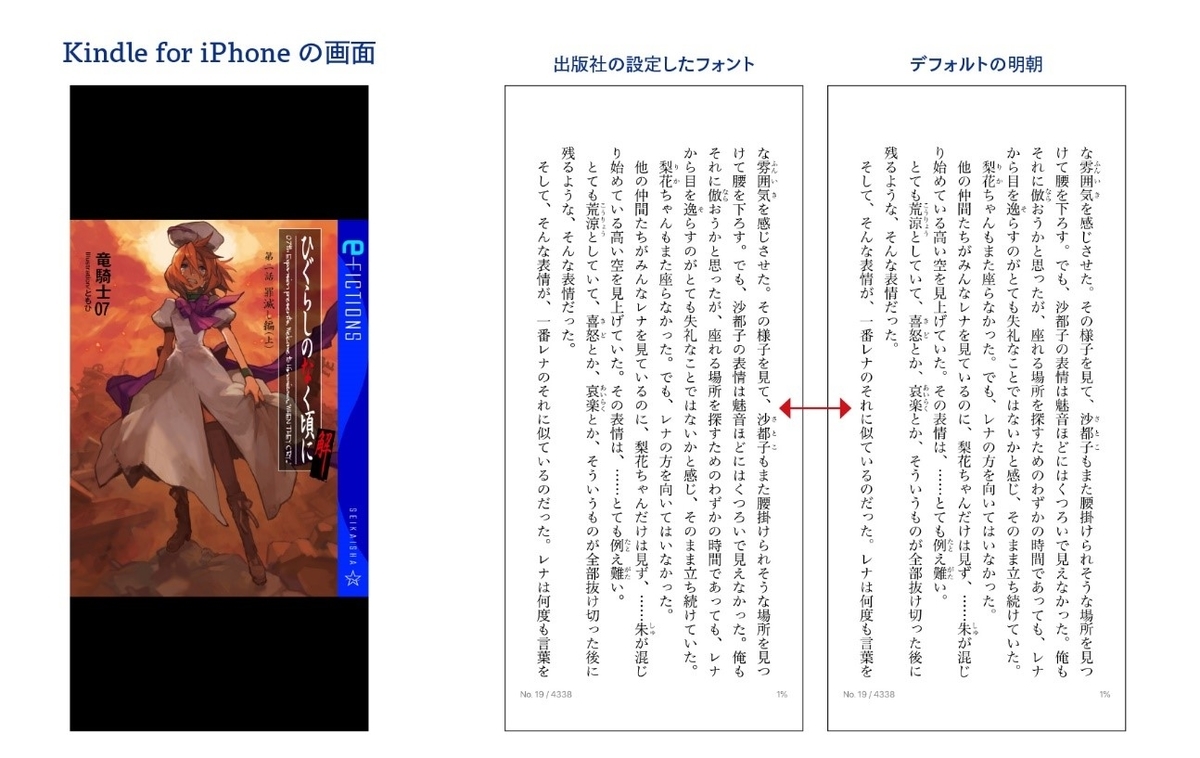
▼星海社オリジナル電子書籍専用フィクション用かなフォント「フミテ」開発アドバイザー京極夏彦氏からのコメント。
フミテとは、「筆」の古語。人から人へと想いを伝えるテクノロジーの根源にあるべき熱量を、この日本初の電子書籍専用書体は見事なまでに継承し、体現しています。先駆けとなる今回の事例に続く新たな挑戦によって、電子書籍の世界がさらに魅力あふれるものとなることを期待しています。
電子書籍専用フォント「なぎ(凪)」
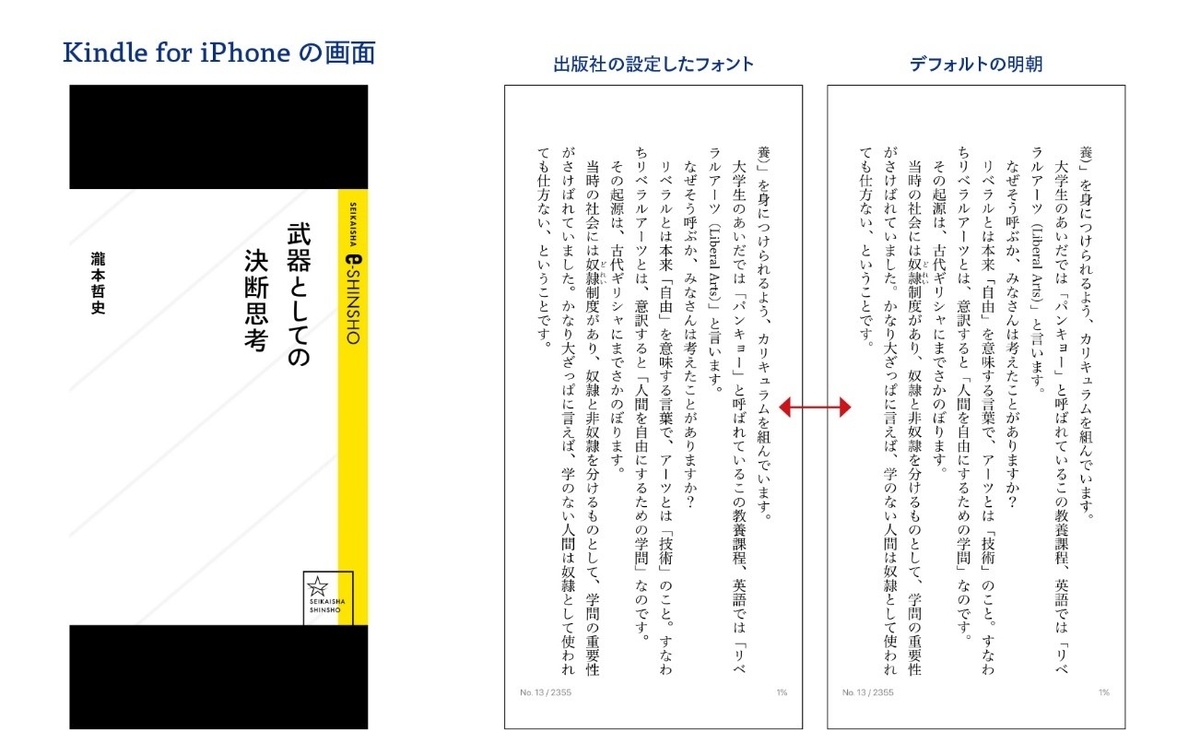
▼星海社オリジナル電子書籍専用ノンフィクション用かなフォント「なぎ」開発アドバイザー古賀史健氏からのコメント。
「読むノイズキャンセリングヘッドフォン」。この書体にキャッチコピーをつけるなら、こんなことばがふさわしいと思います。視覚的なノイズを極限まで排し、知の修得をいっさい妨げない、ニュートラルな書体。湖面に響く鳥の声にも似た、静寂の書体。そんな第一印象を頼りに、水面に波の立たないおだやかな状態を指す「凪」から、この名を選びました。